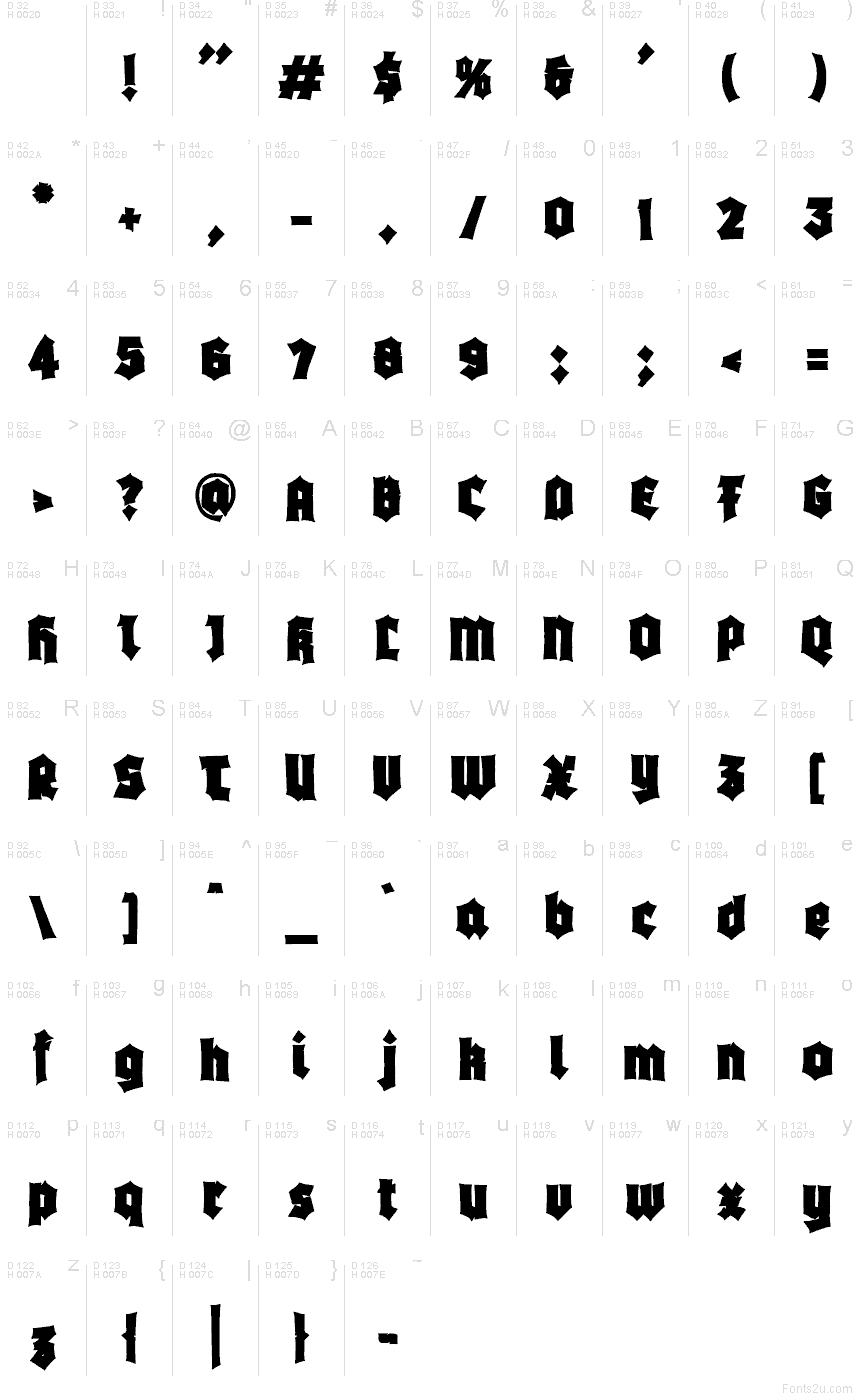
New Order Company
La police New Order Company, créée par Woodcutter Manero, est une police gothique gratuite arborant des formes blackletter acérées et angulaires, avec des coupes nettes qui lui confèrent une forte empreinte médiévale. Les lettres se distinguent par leurs pics pointus, leurs courbes massives et leurs encoches franches, conférant à l'ensemble un aspect rigide et stylisé tout en conservant une belle dynamique.
New Order Company est idéale pour les titres d'affiches, les visuels musicaux, le branding de jeux vidéo, les logos et la signalétique événementielle nécessitant une ambiance sombre et historique. Cette police gratuite convient également aux créations de tatouages et aux designs d'étiquettes, car ses formes brisées et ciselées possèdent suffisamment de caractère pour asseoir les textes courts en grand format.